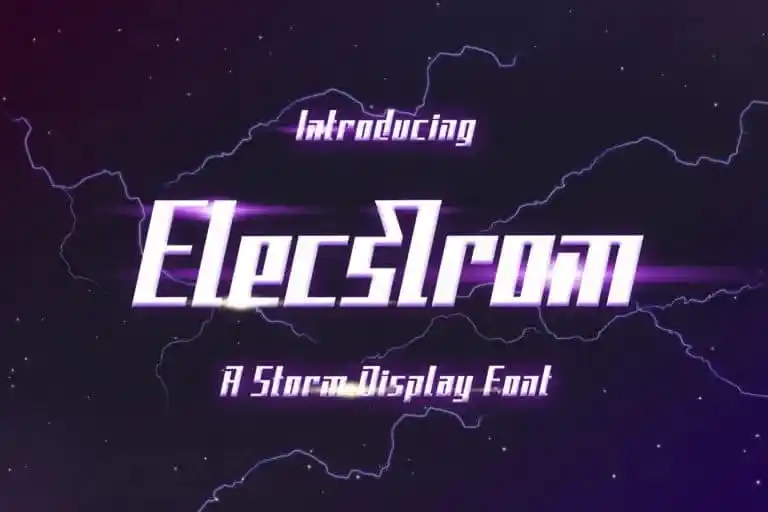
Elecstrom Display Font – Download Grátis
A Elecstrom Display Font é uma fonte compacta criada pela typefactory. Ela carrega com ela a sensação de um tempo inclemente, mas oferece experiências atraentes e descontraídas. Essencialmente perfeita para aplicações em capas de produtos, sinais de trânsito, capas de álbuns ou até mesmo jogos e filmes com temas cativantes, ela é uma escolha ótima para quem procura um estilo inovador e impactante. Seu uso na comunicação visual pode resultar em design capturando a atenção do público, seja ele em mídias digitais ou impressas. Sua característica de acabamento compacto a torna uma opção versátil que encaixa-se perfeitamente no estilo moderno e atemporal da typefactory.